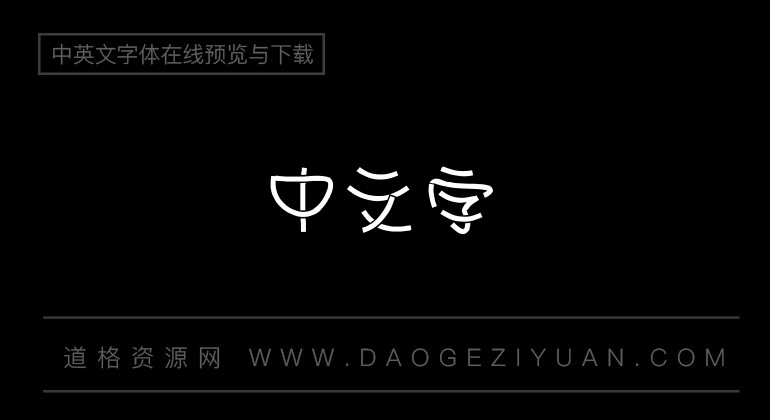
金梅浪漫小叠字体
金梅浪漫小叠字体是一款极具特色的汉字字体,它采用叠字形式,把汉字字形变得浪漫、优雅,极具艺术感。字体笔画细腻,符号清晰,结构设计精细,极具科技感,具有良好的可读性和可辨识度,可以用于报纸、杂志、书籍等出版物的排版,也可以用于广告、宣传物料的设计。
金梅浪漫小叠字体是一款非常不错的手写艺术字体,具有很好的视觉感,适合于文化类的宣传设计、商业类品牌的广告和产品包装设计以及个性化文字排版等较多场景。